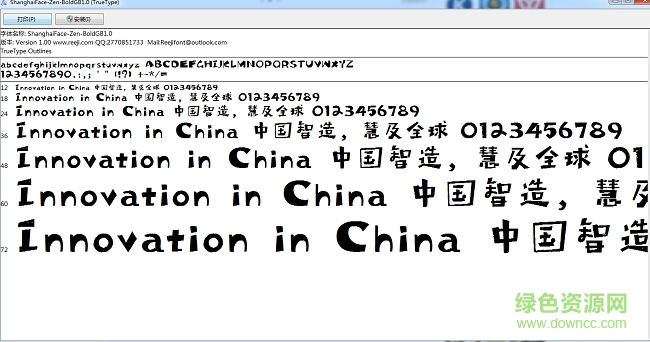
shanghaiface zen boldgb1.0字體是一款由銳字工房推出的海派腔調禪粗黑簡1.0字體,筆畫干凈利索,黑白對比強烈,腔調十足,極具美感,歡迎喜歡的朋友免費下載使用!
海派腔調禪粗黑1.0是在海派腔調藝術黑的基礎上,進一步減小筆畫的粗細對比性,在進一步增強通用性的基礎上保留了原有的結構的狀態(tài)。
字體采用疏松的結構,整個字形的通透性很強,使人看后心情放松愉悅;與傳統(tǒng)字相反的疏密處理方法,增加了每個字的趣味性;筆畫中的小點減輕了復雜筆畫的重量,使字態(tài)輕盈;筆畫雖散,但結構緊湊,整個字形散神不散。